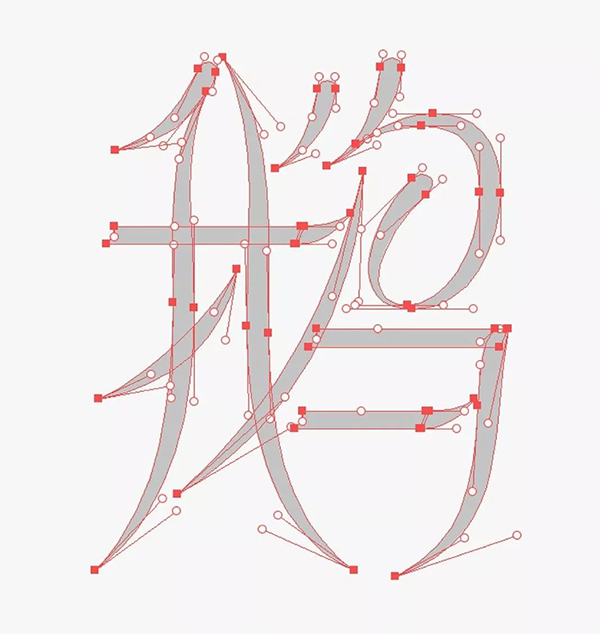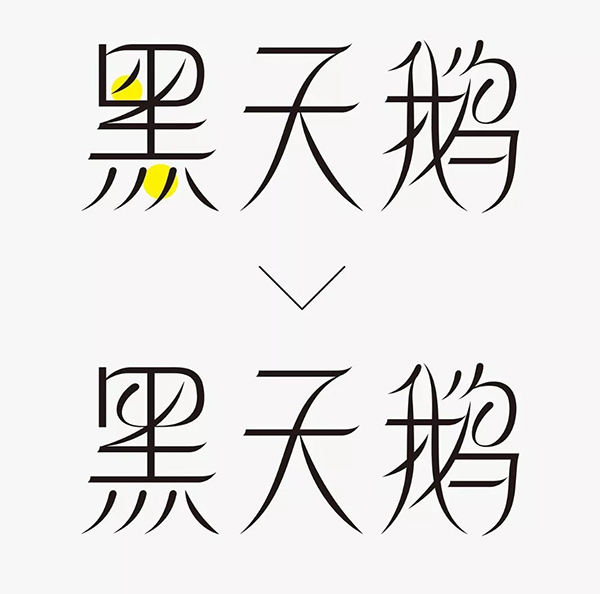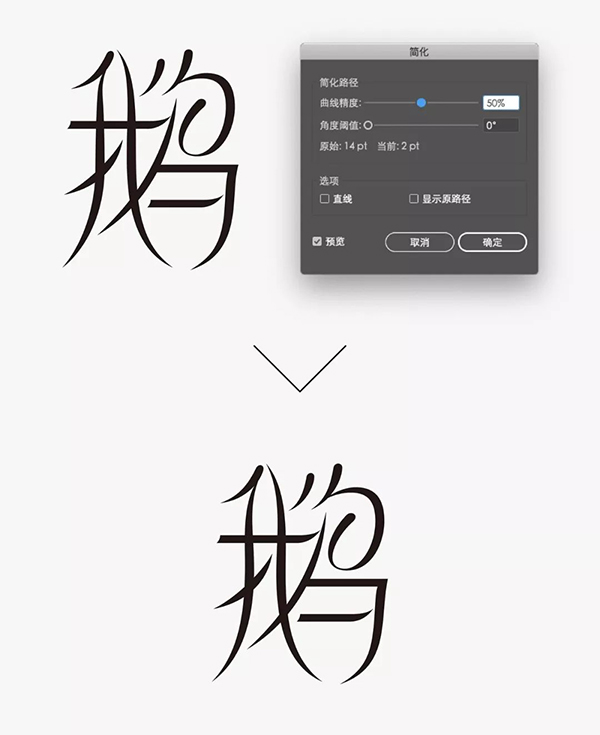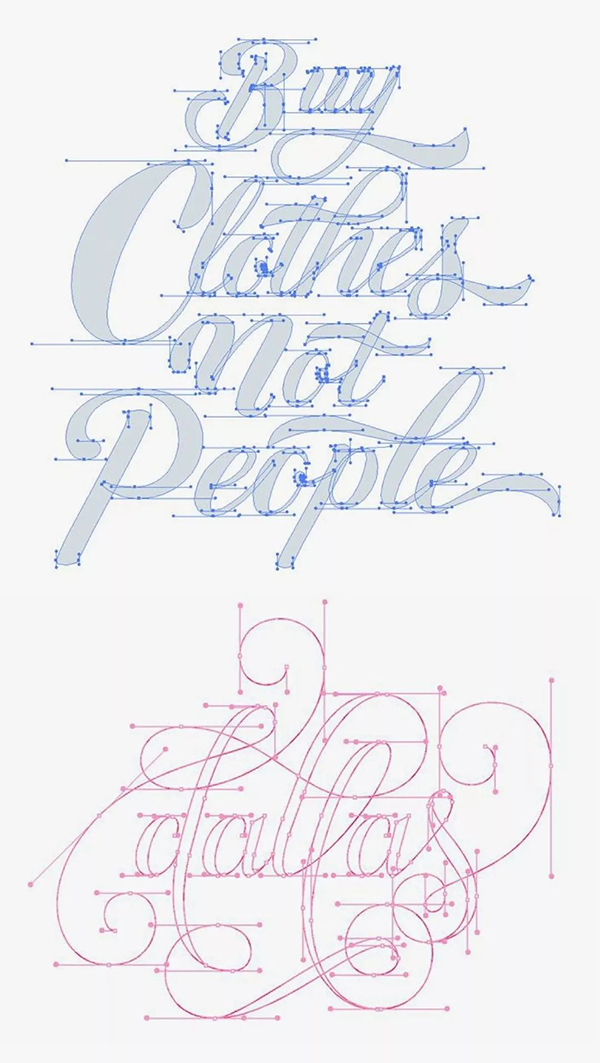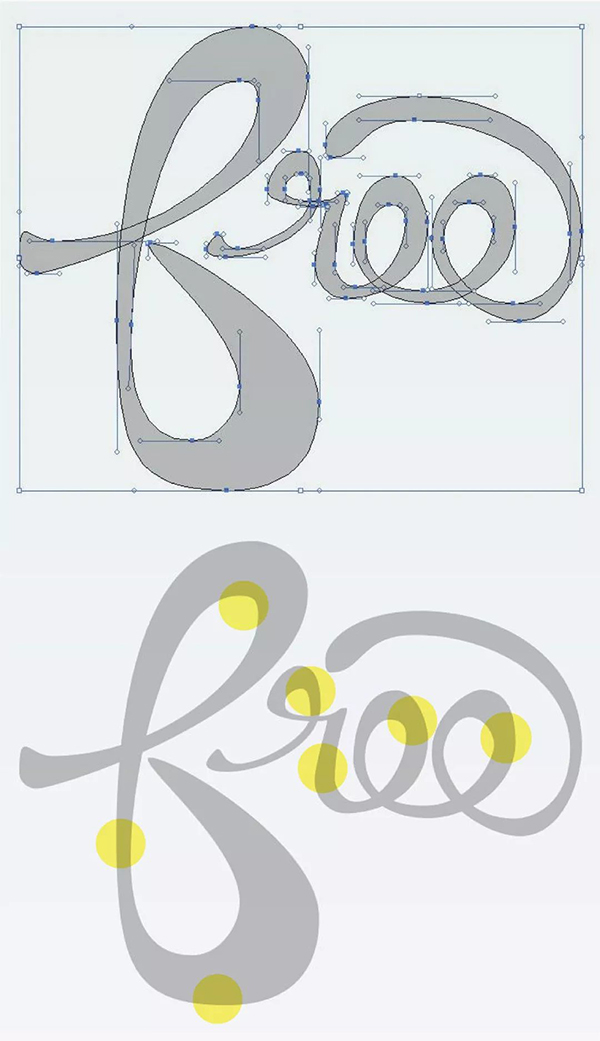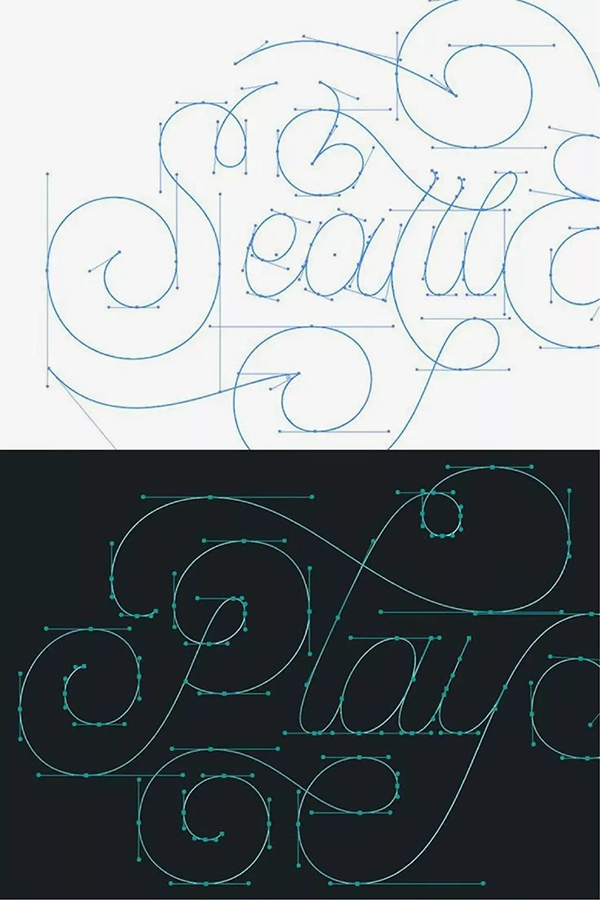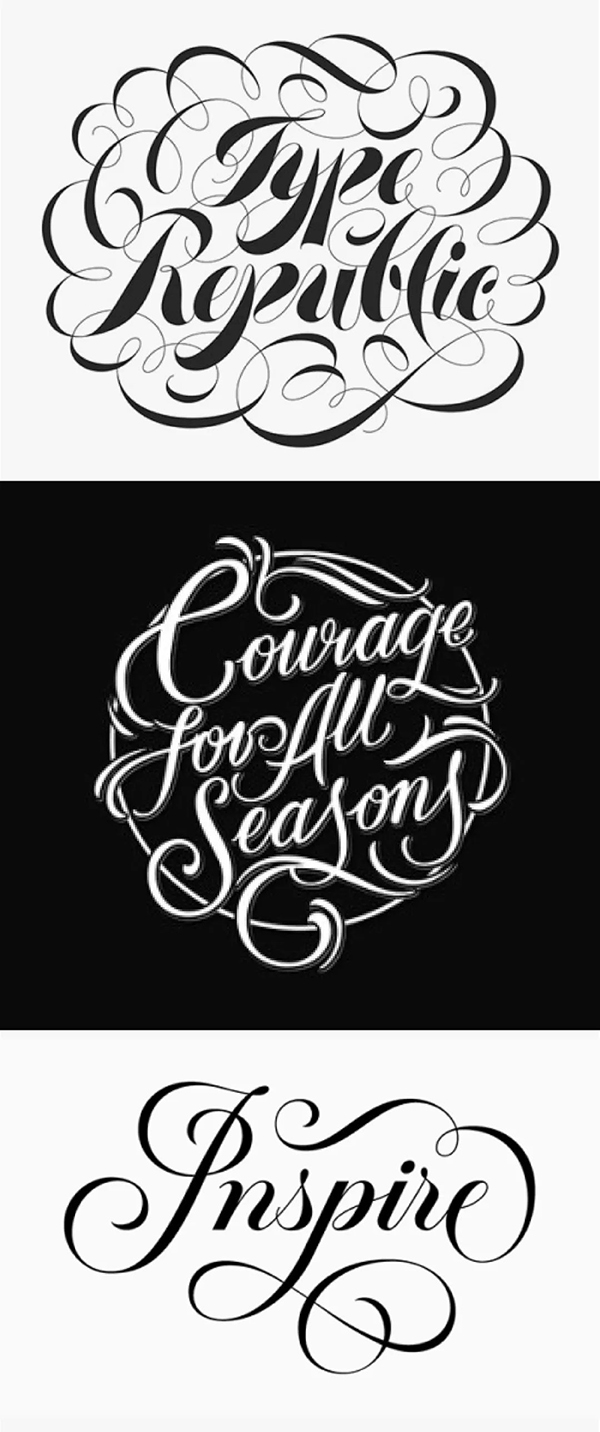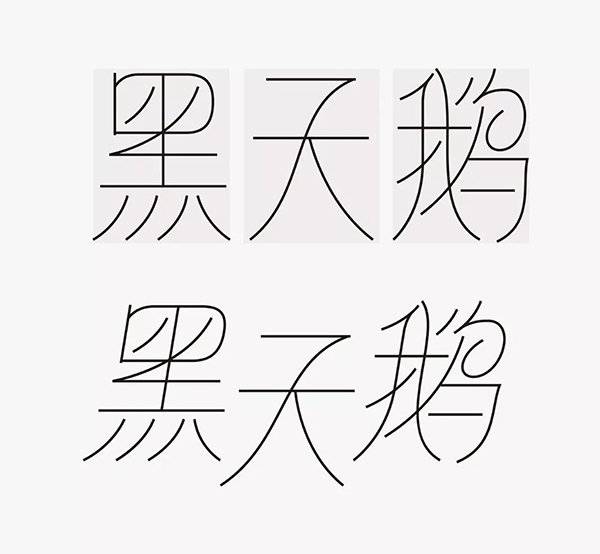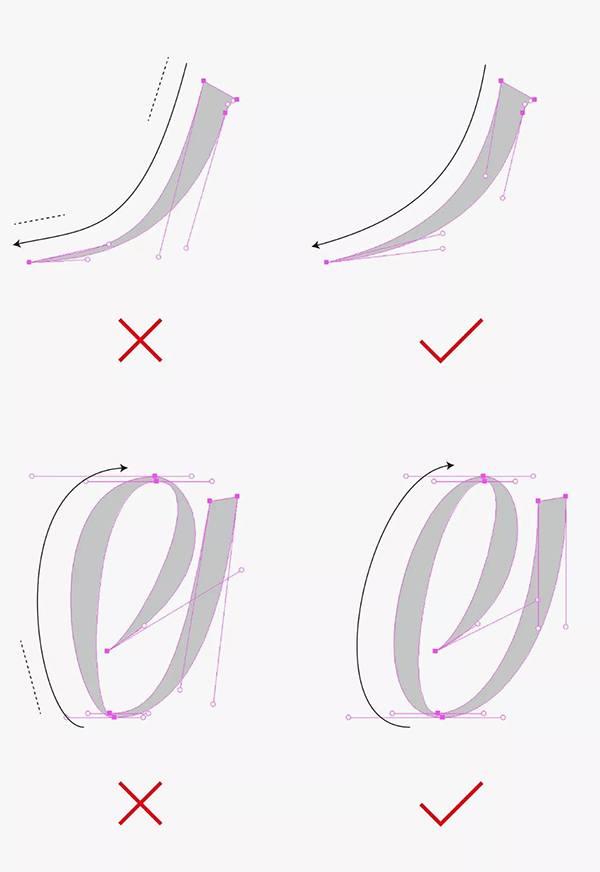
绘制字体曲线的3个诀窍、N项技巧字体资讯
线条是字体最基本的组成部分,其除直线外,曲线的绘制成为做字的重点,同时也成为一大难点。曲线品质的好坏直接影响到字体作品的优劣
但很多同学还是比较迷茫,不知如何下手,并且无法分辨自己绘制的曲线是否正确?有时会花费半天或者一天的时间来调整曲线,然而效果还是非常差……想“死”的心都有!
下面我们详细来聊一聊,绘制曲线的诀窍。
怎样的曲线是舒服的
“舒服”这个词是比较抽象的,我们无法制定出一种标准来衡量你做的曲线,给人的感受是舒服的。但可以总结出一些规律,来帮助大家能有的放矢的做出一条不那么劣质的曲线。
我整理出了三个诀窍:布点、手柄和流畅,可能有些太抽象,接下来且听我娓娓道来。
一、布点
首先,“布点”指的是锚点的位置,对于大范围的螺旋曲线来讲,锚点分布在曲线的极值点上,也就是曲线中位于水平与垂直的点,这在西文的花体中能直观的看到,而且锚点的分布疏密要均匀。
在中文字体中,我们可以将撇、捺笔画理解为曲线,很少情况会将其做如西文花体那样大范围的曲线,此时上文的取点方式就不再适用,只需在曲线的两端取点即可,不要在中途取点。
二、手柄
其次,“手柄”指锚点的操控杆,同样可分为两种情况,对于如花体那种大范围的曲线来讲,两端手柄都要延伸出去,切记不要一端手柄极长,一端手柄极短,两端手柄长度协调为易,这样绘制出的曲线才会流畅。
对于小范围的曲线来讲,可以只激活一端的手柄,这样可以简化绘制曲线的难度,从而提高我们调整曲线的效率。
三、流畅
最后是曲线的流畅度,这对初学者来说是最难的一点,调来调去怎么都不理想,直至耗尽自己最后的耐心,只能草草了事了……
其实这对于有一定经验的设计师来讲,也并不是那么容易的,都需要花费较长时间将其调整到理想的状态,其中还是有些技巧来帮助大家确定曲线是否流畅。就是要保证曲线中不要有直线形态的存在,这样绘制的曲线才会流畅。
下图列举出的这款西文字体作品,布点和手柄处理的都没问题,但曲线的流畅度很不理想,问题就出现在他的曲线中存在大量的直线形态,最终导致曲度不顺,较生硬。
以上这三点都能做到后,需要做一些临摹来达到娴熟的目的,大家可以找一些西文的花体进行临摹。
这样一来,想必大家绘制的曲线品质会有质的飞跃,而且又增长了一门辨别曲线优劣的新技能。
需要掌握的三个要点理解后,下面通过,三个『字学堂』“一周一字”活动中命题案例的讲解,总结出4项技巧,让大家加深并吃透其中的原理。
巧用描边样式
"黑天鹅"从字义来看,使用曲线是再合适不过的了。若此时没有好的想法,大脑一片空白的话,我们可以找一些字体作品当作参考,从中汲取养分,化为己用。下图这个“春”字,想必大家都有见过,他这个字中曲线的品质是很高的,其中最显眼的是“日”字的处理,这也是他这个作品中的一大亮点。除此之外还可以观察到,他的横画主体是直线,这样做的目前是为了突出亮点,使得字形有主次之分,增强字体的层次。
对于一些没有手绘能力的人的来说,可以巧用描边来将字体的骨架与曲线绘制出来,之后再由骨生肉,这样会提高做字的效率。
下面我们来观察下“黑天鹅”这三个字的结构,看下哪里可以加入参考作品中“日”字的处理方式。在这三个字都不含“日”字形,只能设法对其他结构简化,才有可能实现,其中“鹅”字的笔画最多,这为简化提供了很好的条件,我们可以先从这个字做起。
“鹅”字中“鸟”的上半部分,可以简化为我们想要的“日”字形;底部的勾画全部调整为曲线形态,以达到增强曲线特征的效果,但注意曲线的弧度是按照字形本身的形态调整的,因此弧度都是各异的;在笔画密集的“鸟”字处进行了简化;为强调撇画的特征,将“我”字的点画调整为撇;最后为进一步凸显曲线的柔美,选择一笔幅度较大笔画,将其调整为弧线,并将字体的重心提高,中宫内收。
再单独详细看下“鹅”字骨架中曲线的路径状态。
这样通过笔画最多的字,确定出了字面的大小,方面我们去设计前两个字,并且撇画与弧线的特征在其他两字中也要有所体现。故为增多撇画的形态,将“黑”中点画的方向进行调整。同时在“天”字中加入弧线。
这样初步的字体骨架就设计完成了,其实这完全可以作为一个完成稿。
A、“描边宽度配置样式”可降低曲线难度
接下来,可以使用软件自带的描边宽度配置样式。
对字形中所有撇画形态进行调整,这在一定程度上可以简化我们制作这类曲线的难度。
笔画统一变换后,将长度较短的撇画,调整为“泪滴”形态。
着重是对“鸟”字亮点处大面积曲线的调整,这种曲线要在转折处加入粗细变化才会优美。
B、“椭圆工具”辅助测量曲线宽度
其中,对于曲线笔画的宽度,很多同学控制不好,我们可以使用“椭圆工具”取出字体中竖画的宽度,将该圆形作为度量曲线笔画宽度的工具。
对于使用描边宽度配置样式的笔画,我们需要先将路径简化转曲后,方可调整该曲线。
单独看下“鹅”字的路径图。
初步完成后观察发觉“黑”字与其他字明显不协调,问题就出现在“黑”字中“口”字形的处理,刚好可以将其调整为亮点的形态,这样问题就迎刃而解了,调整后的字形效果和谐了许多。
最后,将字形整体倾斜,错位编排,使字形整体更为饱满,并添加西文字体,这样该案例的设计就结束了。
部分曲线
我们以“蝴蝶梦”为内容进行设计。大家有时在涉及曲线字形时,有些同学会将所有笔画都调整为曲线形态,如果你调整控制的能力很差的话,这无疑是在给自己挖坑,通过收到的作业也能直观的看到,调整不充分字形会显得松散无力。
我们可以另辟蹊径,不要让笔画都带有曲线,只保持部分笔画带有曲线,这样设计的难度系数会降低很多,字形会产生层次感,从而达到美观的效果。
下面来看下本次要做的“蝴蝶梦”这三个字的结构,前两个字的笔画较多,尤其是“蝴”字,可以考虑在笔画密集处使用简化。
C、软硬对比方可凸显曲线
先采用描边方式将“蝴”字设计出来,字形整体保证上端硬,下端软的规律,仅在简化处使用大范围的曲线,这样设计出的字形在统一中带有变化。
而后把其余两字设计出来,将起到简化作用的类螺旋纹,作为整组字的主要亮点,保证在每个字体中有一处出现,其中“梦”字并未找到好的处理方式,只是将撇画进行了延长,这样亮点结构规律性集中出现字体的底部。
在横画起笔处加入微小的弧线,以进一步增强字形整体的特点,
接下来由骨生肉,可先将描边字形中的竖画增宽,以确定竖画宽度,而后统一调整。为把控曲线宽度,可制作一个度量的圆形,其中“梦”字的螺旋线并未起到替换笔画的作用,故将其宽度设定的较细。其余基本笔画的形态同样要注意曲线的流畅度。
单独看下“蝴”字的路径图。
字形统一倾斜后发现“梦”字不够饱满,故将螺旋线的范围增大,这样整体效果和谐了很多。
通过简单的图形调整,增强螺旋线的穿插关系,使得曲线明朗了很多,并搭配与字形特征相近的西文字体,该案例的设计就结束了。
曲线之美
以上两个案例都含有螺旋的构造,这种结构其实使用的频率并不是很高,更多的是字体结构本身的曲线之美。
我们以“野玫瑰”为内容进行设计,着重在于塑造字形本身的曲线。同样先观察下字体的结构,结合宋刻体,营造出手写的感觉。注意“玫”字交叉点对重心的影响。
同样采用描边方式将字体的骨架设计出来,其中部分竖画调整为曲线构造,以营造手写感。
结构确定后,将笔画形态设定的尖锐、夸大些。
将描边结构作为辅助,将体饰添加进去。
D、曲线类笔画粗细变化不要过急
这种曲线都是在收尾两端曲线,切记不要在中途取点,注意弧度对曲线弹性的影响,下图可观察下字形的路径图。其中,撇、捺曲线类笔画粗细的变化要协调,不要变化过急,要有较缓的变化过程。
集中对间架结构与曲线不理想的“野”字进行调整。
对字形整体进行倾斜,并调整字间距,使其更为紧凑。
这款比较张扬狂野的字形的设计就结束了。
以上我整理出3个诀窍、4项技巧,并通过3个案例讲解,由浅入深,向大家介绍字体中曲线该如何高效的绘制,希望大家能有的放矢,不再迷失方向。